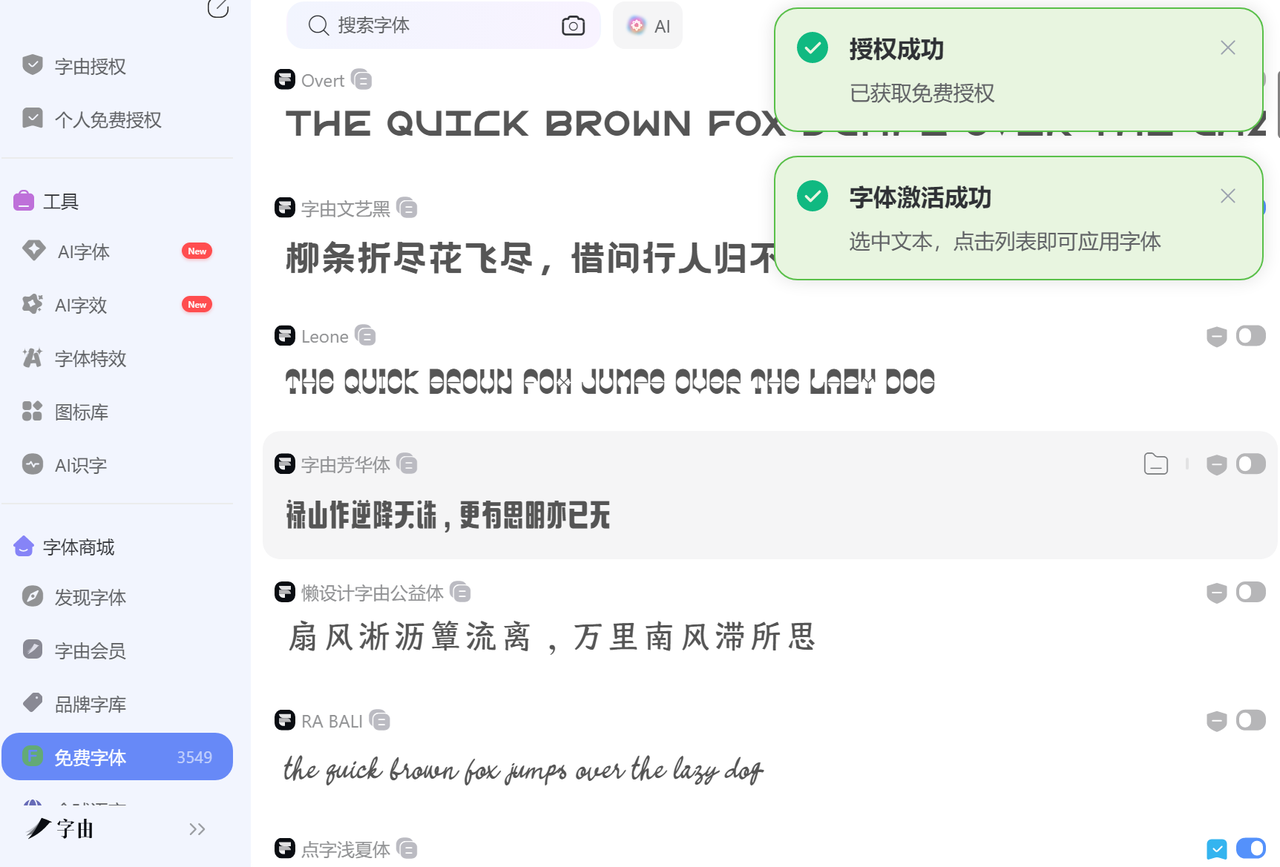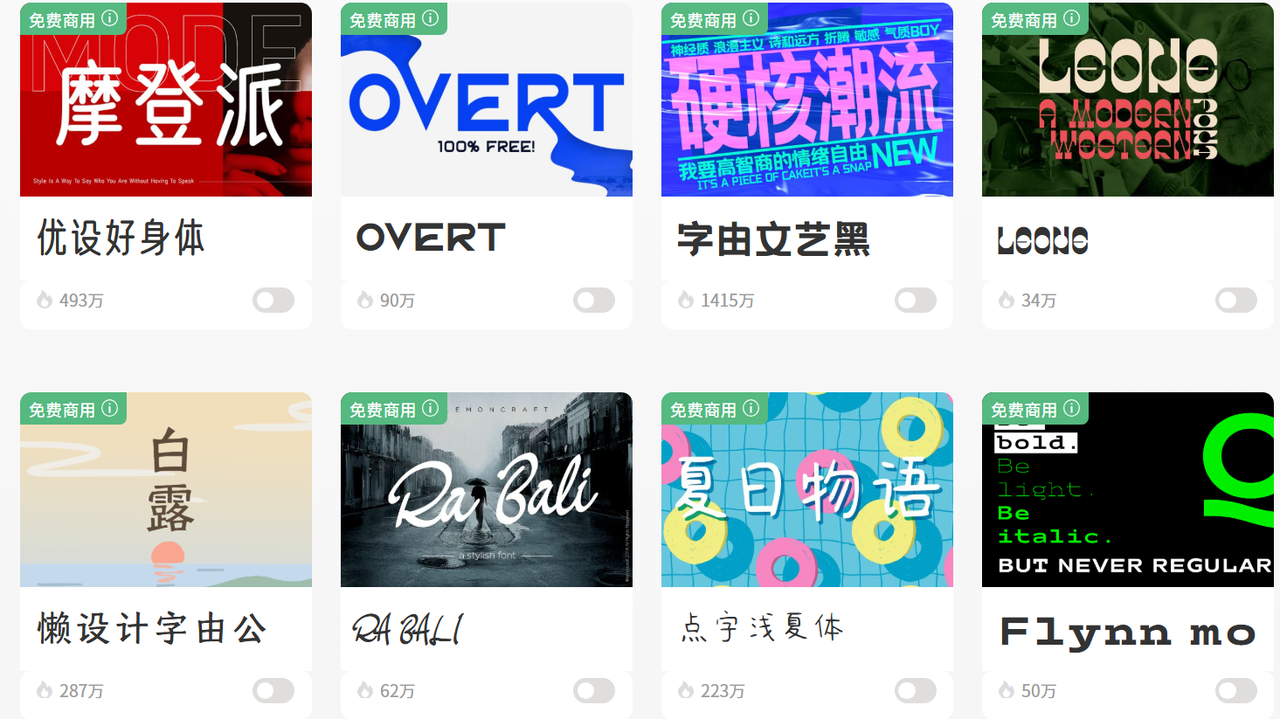
adobe 中文字体网站分享,放心用不踩坑
字体在设计领域这个颜值定胜负的赛道中,是不可或缺的核心要素。一款适配的 adobe 中文字体,不仅能精准传递设计的核心表达,更能拉升整体画面质感、契合创作的专属调性。不少朋友总觉得找正版适配的 adobe 中文字体是件麻烦事,费时又费力,但别担心,我今天就来给大家推荐几款不管是设计新手还是资深从业者,都能轻松上手、高效取用的 adobe 中文字体下载网站。
字由网
作为深耕字体服务多年的平台,字由网是超百万设计师的高频选择,适配Adobe全系列软件的特性的让它成为首选,完全不用费心适配调试,新手也能快速上手。
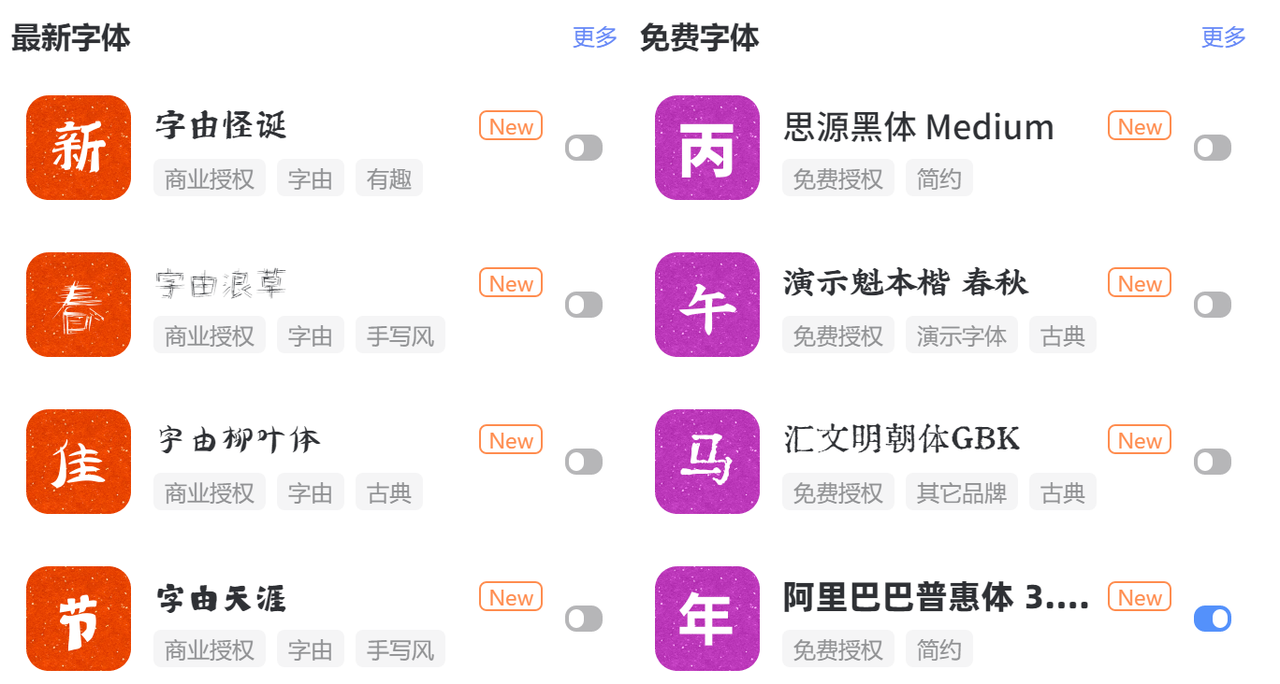
Adobe Font 官网
作为Adobe官方字体平台,与Adobe全系列软件深度原生适配,无需额外调试,是Adobe用户的官方优选。平台坐拥30000+款全球优质字体,涵盖海量中文字体,包含Adobe Originals原创系列字体(如思源宋体衍生优化版),支持七种字重调节,覆盖GB18030 2022实施等级2规定的所有汉字,适配多场景排版需求。
站酷字体库
站酷字体也是我常用的字体平台,也是设计师聚集地的专属字体库,所有中文字体适配Adobe软件,字体风格偏向创意化、个性化,涵盖手写体、复古体、潮流体等多种小众风格,适合海报设计、新媒体配图、LOGO创作等场景。字体安装后能直接在Adobe软件中调用,不会出现显示异常的问题,还能查看其他设计师的字体使用案例,参考性强。
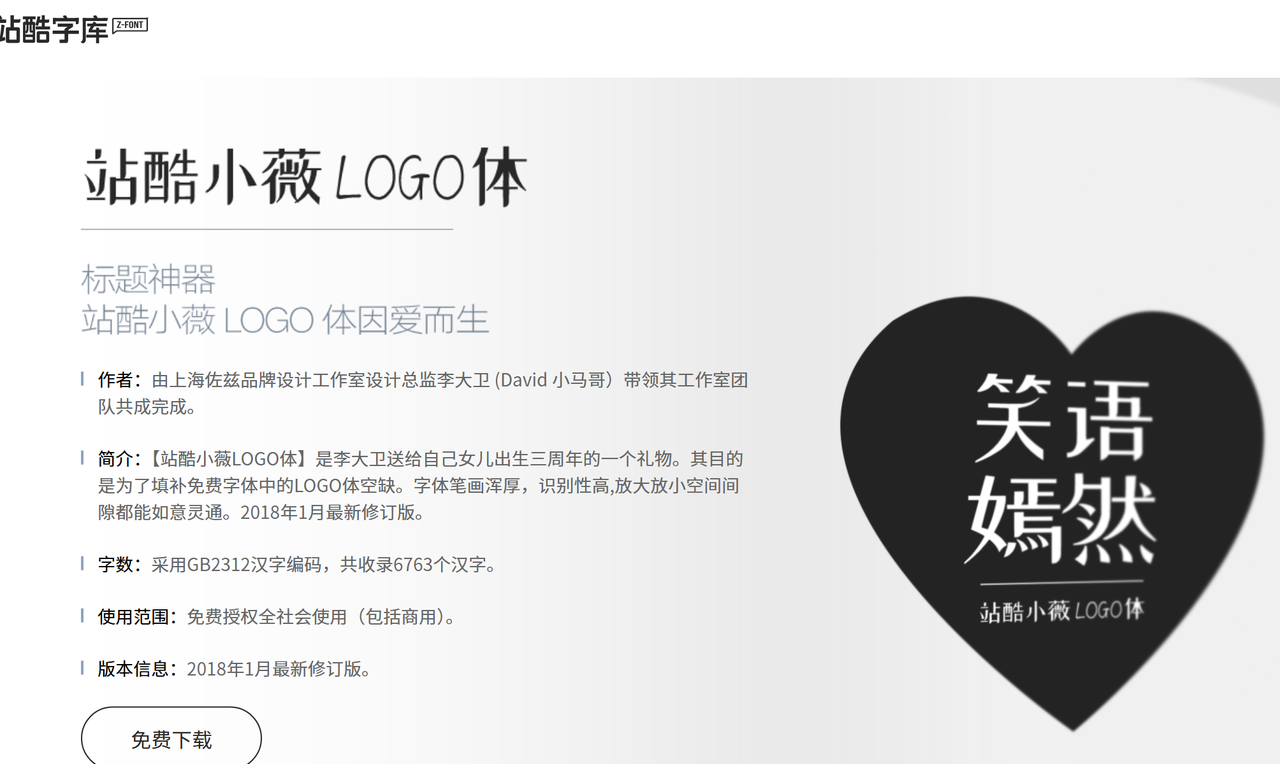
汉仪字库官网
汉仪字库的官方平台字体资源更全面,主打正版商用,中文字体适配Adobe全系列软件,适合企业用户、高端设计需求。字体风格涵盖商务、文艺、复古、童趣等,每款字体都有详细的授权说明。字体兼容性经过严格测试,在Adobe软件中排版流畅,导出作品时不会出现字体变形、错乱的问题,还能定制专属字体,满足品牌差异化设计需求。